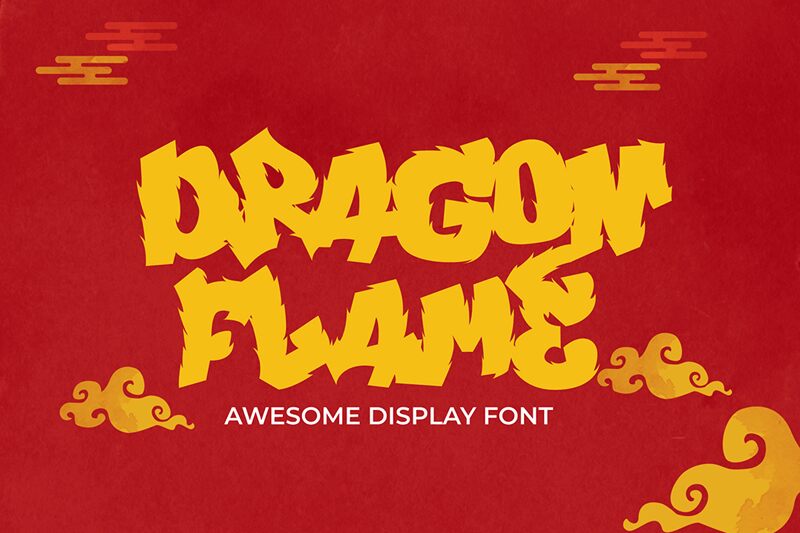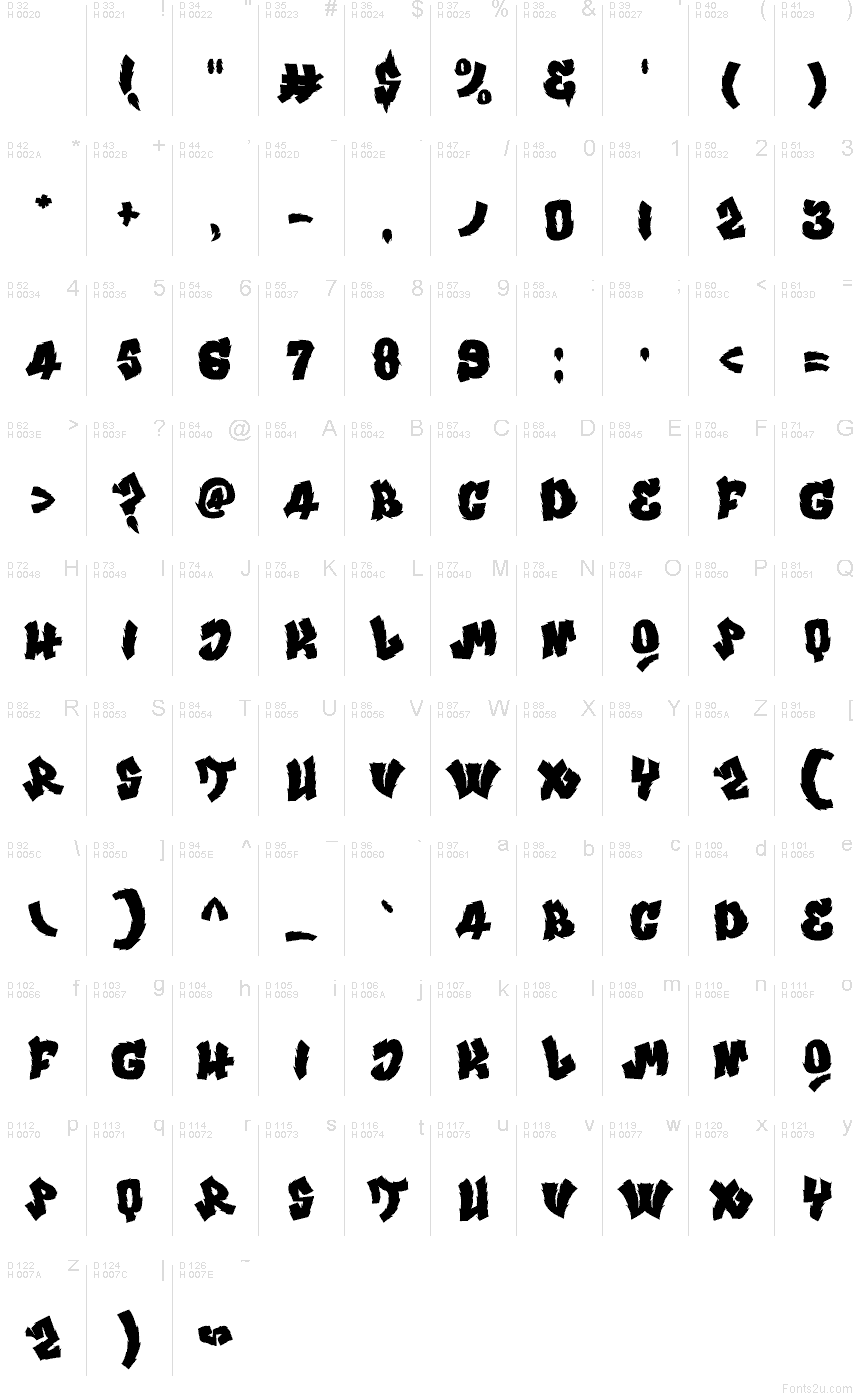
يعد Dragon Flame من Sipanji x Figuree خط جرافيتي مجاني يتميز بظلال مسننة تشبه ألسنة اللهب، مما يمنح الحروف مظهراً محروقاً ومتأثراً بالرياح. تمنحه الزوايا غير المنتظمة والحواف الممزقة والأشكال السوداء القوية طاقة خام تشبه الكتابة بالبخاخ على الجدران، بعيداً عن أسلوب خطوط الكوميكس أو الهيب هوب التقليدية.
هذا المظهر الهجومي مثالي لأغلفة الألبومات، وتصاميم ملابس الشارع (ستريتوير)، وملصقات الألعاب، وعلامات التزلج، ونشرات الفعاليات، حيث يحتاج النص إلى إحداث تأثير بصري سريع. يبرز الخط بشكل أكبر في العناوين القصيرة والشعارات، حيث تخلق الحواف الحادة إيقاعاً ديناميكياً يضفي على الكلمات مظهراً جريئاً وحيوياً.